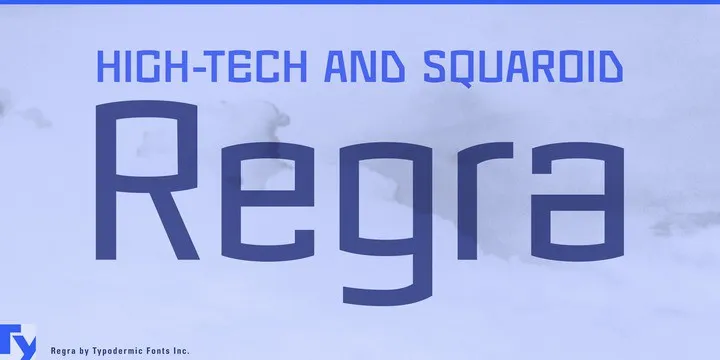
Regra Font Family
A fonte ‘Regra Font Family’ é uma família de tipos digitais projetada para expressar modernidade e tecnologia contemporânea. Com seu design curvado em quadrados, ‘Regra’ representa um estilo display que se destaca por sua simplicidade angular e presença forte. Esta fonte é ideal para elementos visuais como títulos de página ou menu, oferecendo um contraste vibrante que chama a atenção no layout. Desenvolvida pelo designer Hamilton, a ‘Regra Font Family’ abrange uma gama de tipos adequada tanto para aplicações digitais quanto impressas, mantendo sua agressividade e modernidade em qualquer formato. Seja você um criador de conteúdo digital ou um profissional da design gráfico, essa fonte é uma ótima escolha para dar seu projeto aquele toque único e tecnológico que o torna destaque na web.